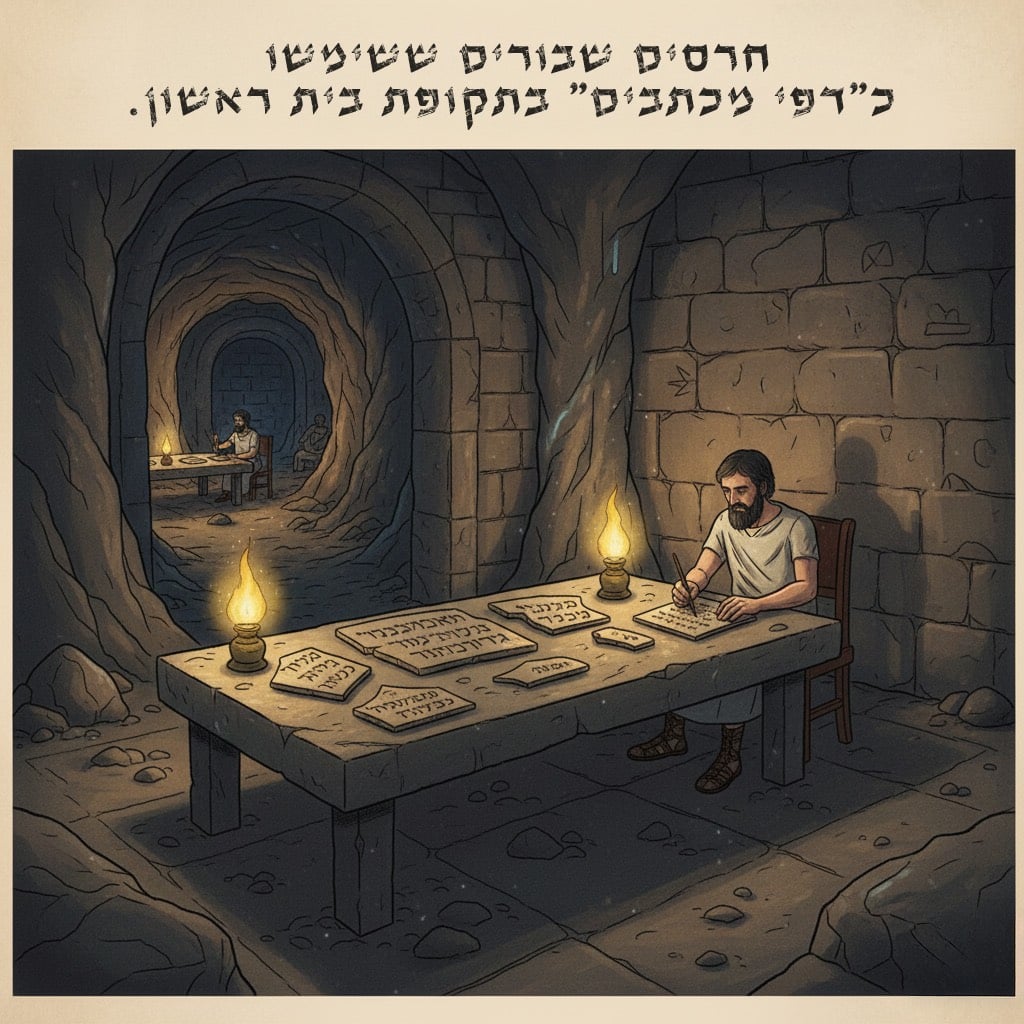
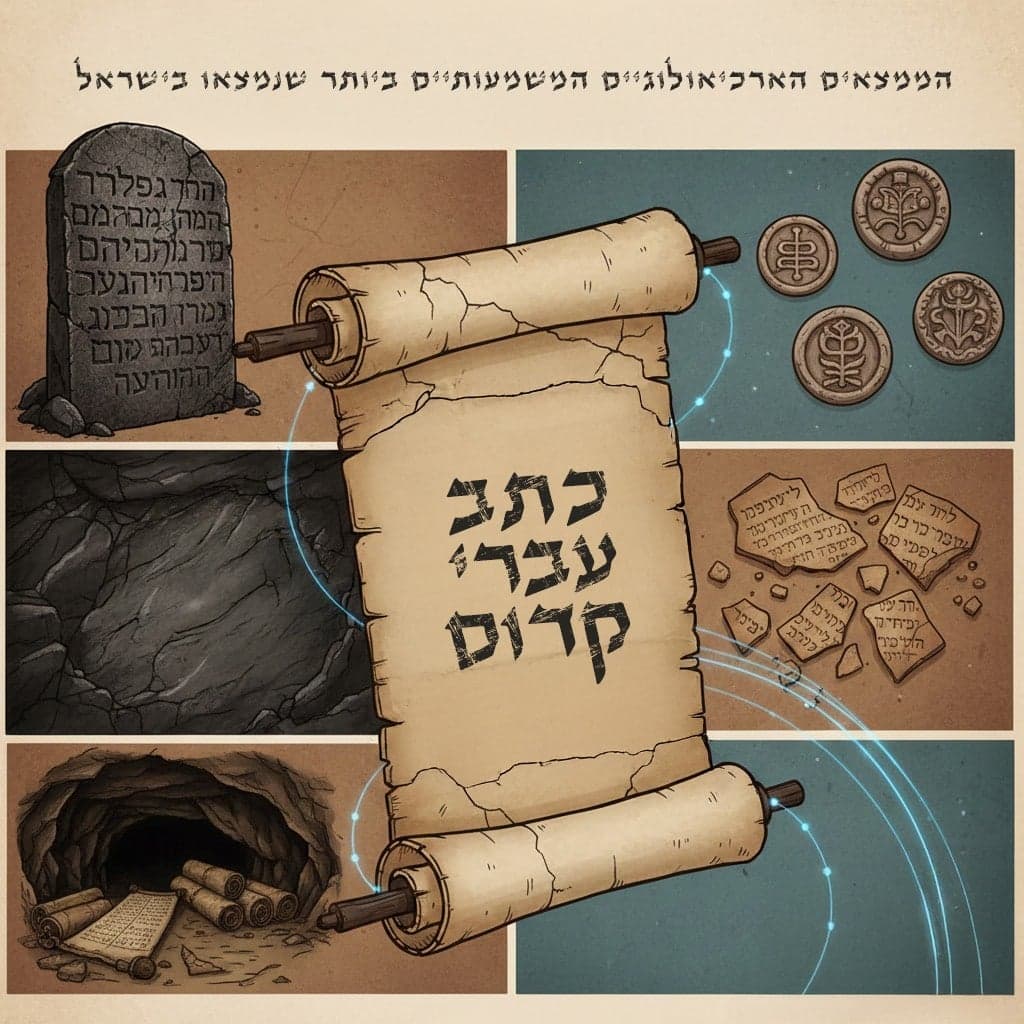
הארכיאולוגיה הישראלית חשפה לאורך השנים ממצאים מרתקים המעידים על התפתחות הכתב העברי מראשיתו ועד ימינו. כתב עברי קדום מהווה חלון ייחודי להבנת התרבות, השפה והחברה של עם ישראל בעת העתיקה.
כל ממצא ארכיאולוגי בין אם מדובר בחרס שבור, בכתובת על סלע או במגילה עתיקה מספר סיפור על האנשים שכתבו, על מה שחשוב להם ועל האופן שבו תיעדו את חייהם.
המפגש עם כתבים אלה אינו רק מחקר מדעי, אלא גם מסע מרגש בזמן אל שורשי הזהות היהודית.
כל אות חקוקה וכל סימן שנשתמר חושפים עוד נדבך בהתפתחות השפה, האמונה והמורשת, ומזכירים לנו עד כמה עמוק השורש התרבותי של הכתב העברי בעולם העתיק.
מגילות מדבר יהודה, שהתגלו בין השנים 1947-1956 במערות קומראן ובאזור הים המלח, מהוות את הממצא המשמעותי ביותר של הכתב העברי הקדום שהתגלה אי פעם.
למעלה מ-900 מגילות ושברים נמצאו באזור, כשחלקן מתוארכות למאה ה-3 לפני הספירה.
המשמעות של הממצא הזה חורגת מעבר להיסטוריה: המגילות שימרו צורות כתיבה שונות של העברית, כולל הכתב הפליאו-עברי והכתב הריבועי המוכר לנו היום.
לפי מחקרים פליאוגרפיים, ניתן לזהות לפחות 5 סגנונות כתיבה שונים במגילות, המעידים על סופרים שונים ותקופות כתיבה שונות. כל מגילה היא בעצם אוצר של פונטים כתב יד בעברית מלפני אלפיים שנה.
הכיתוב המונומנטלי על מצבת מישע (המואבית), המתוארכת למאה ה-9 לפני הספירה, מהווה דוגמה יוצאת דופן לכתב פליאו-עברי.
כתב עברי קדום שנמצא בירדן אך רלוונטי ישירות לתולדות ישראל, כולל 34 שורות המתארות את מלחמות מלך מואב נגד ישראל. הכתב במצבה זו הוא סדיר, מסודר וברור – כמעט כאילו תוכנן מראש להדפסה.
מה שמייחד את כתב מישע הוא האחידות שלו: האותיות כתובות בגובה דומה, המרווחים בין המילים שמורים בקפידה, והשורות ישרות.
ארכיאולוגים מעריכים שהסופר השתמש בכלי עזר למדידה כדי ליצור כיתוב מושלם זה. כיום, צורות האותיות ממצבת מישע משמשות בסיס לעיצוב גופנים דיגיטליים המדמים כתב עתיק.
בשנת 1880 התגלתה במנהרת חזקיהו בירושלים כתובת שילוח – כיתוב בן 6 שורות המתאר את חפירת המנהרה. הכתובת, המתוארכת לסוף המאה ה-8 לפני הספירה, נחשבת לאחד הטקסטים העבריים הקדומים והמשמרים ביותר מתקופת בית ראשון. הכתב בכתובת זו הוא פליאו-עברי קלסי, והוא מספק תובנות חשובות על אופן הכתיבה בתקופה זו.
מה שמרתק בכתובת שילוח הוא הסגנון הנרטיבי שלה – זה לא טקסט דתי או מלכותי, אלא תיעוד טכני של פרויקט הנדסי.
הסופר מתאר בהתרגשות את הרגע שבו שתי קבוצות החופרים, שעבדו מכיוונים מנוגדים, נפגשו: "ויום הנקבה שמעו איש את רעהו". זוהי דוגמה נדירה של כתב עברי קדום המשקף רגש אנושי אמיתי.
אוסטרקות לכיש: חרסים שבורים ששימשו כ"דפי מכתבים" בתקופת בית ראשון. 21 אוסטרקות נמצאו בלכיש, רובן מכילות התכתבויות צבאיות מתקופת החורבן הבבלי (586 לפנה"ס).
אוסטרקות ערד: למעלה מ-200 אוסטרקות שהתגלו בתל ערד, המתעדות פעילות מנהלית, צבאית וכלכלית. אלו דוגמאות לשימוש יומיומי באותיות של כתב עברי קדום על ידי פקידים ואנשי צבא רגילים.
חותמות ובולים: מאות חותמות אישיות עם שמות עבריים נמצאו ברחבי הארץ, מעידות על תרבות כתיבה נרחבת בקרב האליטה.
קליגרפיה עברית עתיקה לא הייתה רק אמצעי תקשורת, אלא גם אמנות. סופרי המקרא פיתחו כללים מדויקים לכתיבה, כולל גודל האותיות, המרווחים ביניהן, וצורתן המדויקת. מסורת זו נשמרה עד היום בכתיבת ספרי תורה.
בעידן הדיגיטלי, מעצבי גופנים יצרו פונטים המבוססים על כתב עברי קדום מתוך ממצאים ארכיאולוגיים של כתב עברי קדום אותנטי. גופנים אלו משחזרים את צורות האותיות מתקופות שונות.
שימוש בגופנים אלו מאפשר למעצבים, חוקרים ומורים להעביר את התחושה ההיסטורית של הכתב העתיק.
היום, מעצבי גופנים מפתחים משפחת פונטים שלמה המבוססת על סגנונות היסטוריים של הכתב העברי.
משפחה כזו כוללת וריאציות של משקל שונות (דק, רגיל, מודגש), אך כולן שומרות על האופי ההיסטורי של הכתב המקורי.
התהליך מתחיל בסריקת ממצאים ארכיאולוגיים ברזולוציה גבוהה, ממשיך בזיהוי מאפייני הכתב (זוויות, עוביים, פרופורציות), ומסתיים בבניית גופן דיגיטלי מלא.
חלק מהגופנים מתאימים גם עבור פונטים בעברית לשימוש מסחרי, במיוחד לפרויקטים היסטוריים, תיירותיים או חינוכיים.
כתב עברי קדום אינו רק ממצא ארכיאולוגי הוא המשכיות חיה של תרבות בת אלפי שנים. כל כתובת שהתגלתה מחברת אותנו ישירות לאנשים שחיו בארץ לפני אלפי שנים, לדאגות שלהם, לשמחות שלהם ולדרך שבה ראו את העולם.
הממצאים המרכזיים כוללים את מגילות מדבר יהודה, כתובת שילוח שנמצאה בירושלים, ומצבת מישע שנמצאה בעבר הירדן.
כל אחד מהם מספק עדויות ייחודיות על השפה, הדת והחיים החברתיים בתקופות שונות.
המגילות, שהתגלו במערות קומראן, כוללות למעלה מ־900 כתבים שונים מתקופות שונות. הן שמרו על גרסאות עתיקות של טקסטים תנ"כיים וכתבים דתיים אחרים, וחושפות את מגוון סגנונות הכתיבה ששימשו באותה תקופה.